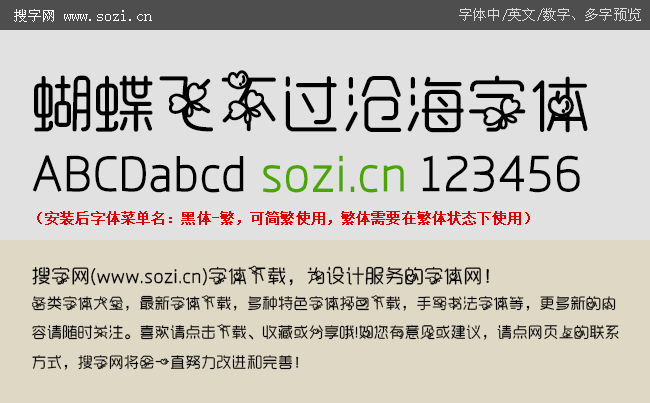
蝴蝶飛不過滄海字體
搜字網(wǎng)給大家提供一款有趣的卡通手機(jī)中文字體下載。這款手機(jī)字體是以造字工房悅黑體字體為原形,在筆畫間插入了卡通蝴蝶圖案。即保持了悅黑的簡約、易識(shí)別的風(fēng)格,又有卡通蝴蝶的趣味點(diǎn)綴,很實(shí)用的一款手機(jī)字體哦。